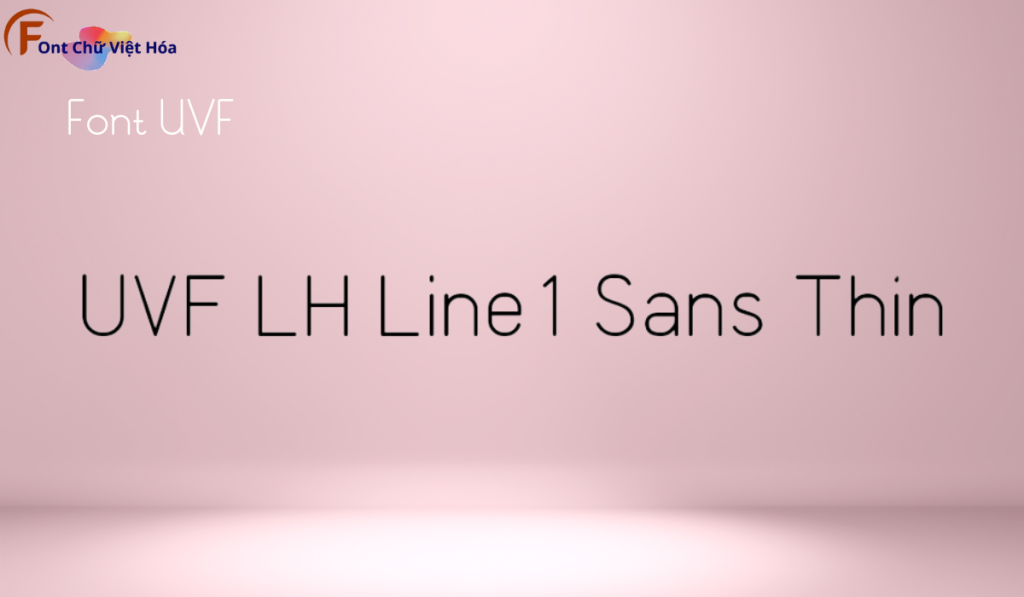
Tai Font Sans-Serif UVF Lh Line1 Sans Thin Việt Hóa
Tác giả: Lh Line1 Sans
Bộ Font: UVF
Độ dày: Thin
UVF Lh Line1 Sans Thin Việt Hóa là font sans-serif với các đường nét thanh mảnh và hiện đại, thuộc bộ font UVF. Font này được thiết kế nhằm mục tiêu tạo ra sự rõ ràng và dễ đọc, đặc biệt phù hợp cho các thiết kế như poster, logo, và tiêu đề. Đặc điểm hình dạng của UVF Lh Line1 Sans Thin là các đường nét mảnh mai và tỷ lệ chữ cân đối, giúp tối ưu hóa không gian và tạo ấn tượng thị giác mạnh mẽ. Font này cũng đã được Việt hóa, mang đến sự linh hoạt và tiện dụng cho các dự án thiết kế bằng tiếng Việt, giúp người dùng dễ dàng tiếp cận và sử dụng.